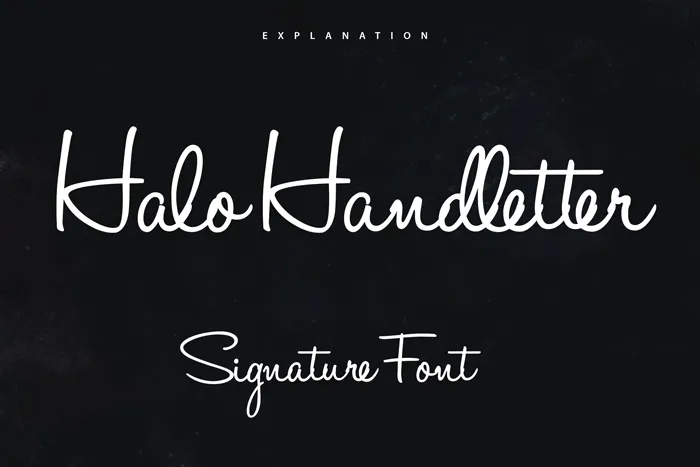
Halo Handletter Font
Aqui está uma descrição envolvente e natural para a página de download da fonte ‘Halo Handletter Font’: Descubra a beleza do hábito de escrever, expressando emoções e sutilezas através das letras que vão desde o básico até a elaborada. Introduzimos Halo Handletter Font, uma elegante escolha para todos os amantes de letra cóncava ou de estilo livre. Desenvolvida pelo talentoso Mario Arturo, esta fonte surgiu da Dover’s série “Brushstroke and Free-Style Alphabets – 100 Complete Fonts”. Ao longo dos anos, essa fonte foi adaptada para a formatos OTF (Open Type Format), eliminando problemas relacionados à geração de espaçamento entre letras. Halo Handletter é uma fonte perfeita para qualquer designer que procura um estilo fluido e único. Ela traz com ela um ar elegante, adequado para uso em anúncios, sites pessoais ou até mesmo em ilustrações digitais. Seja a hora de reviver o encanto das letras manuscritas ou explorar novos caminhos de expressão visual, Halo Handletter é uma escolha irresistível para qualquer projeto gráfico.